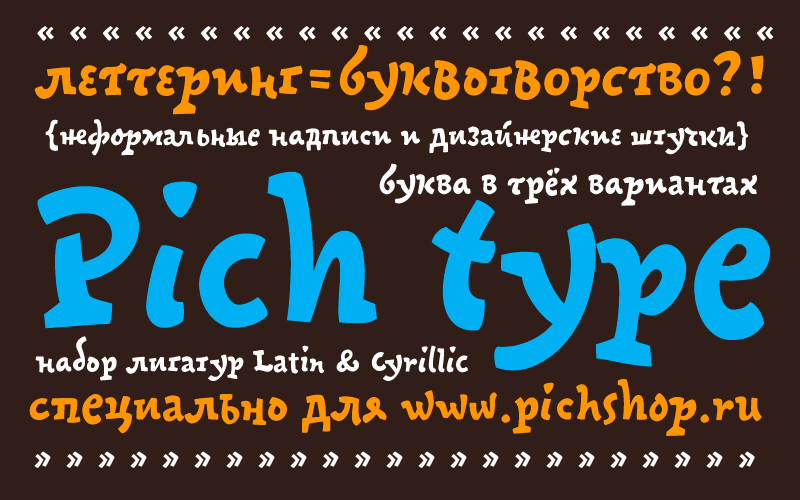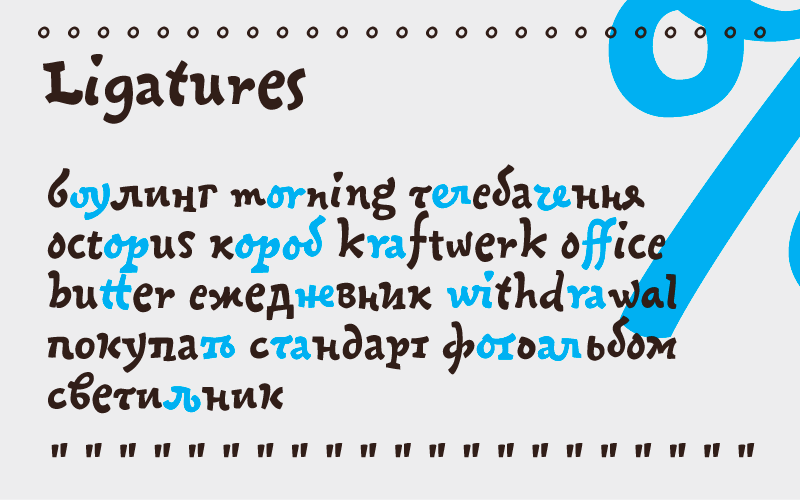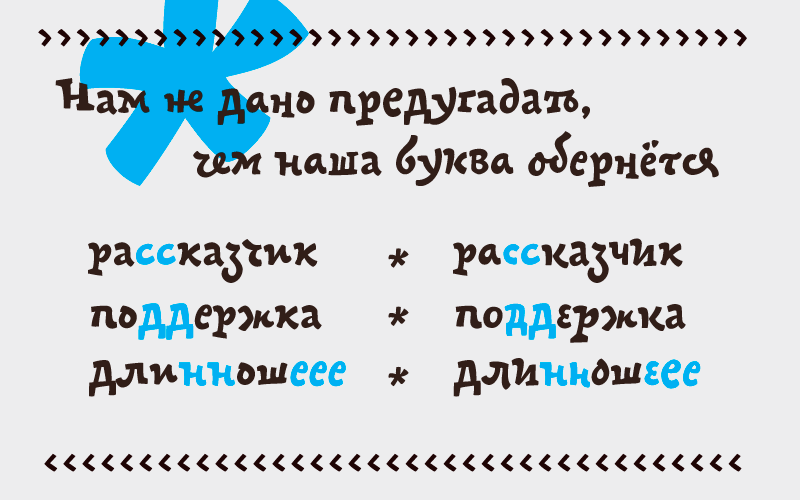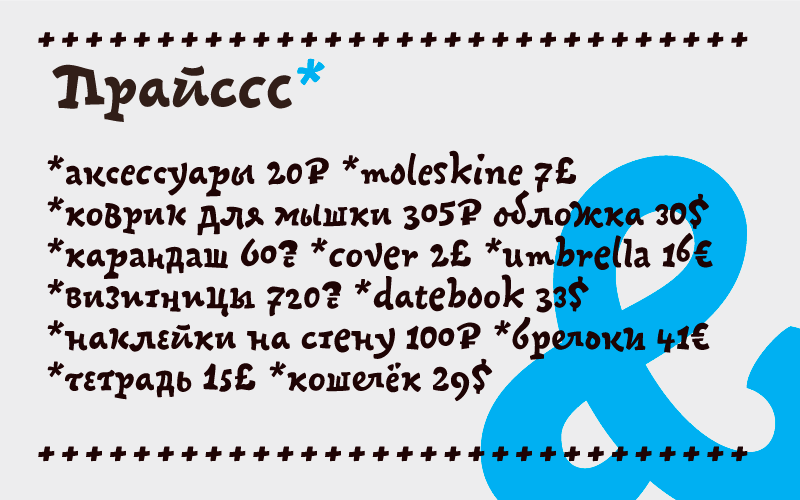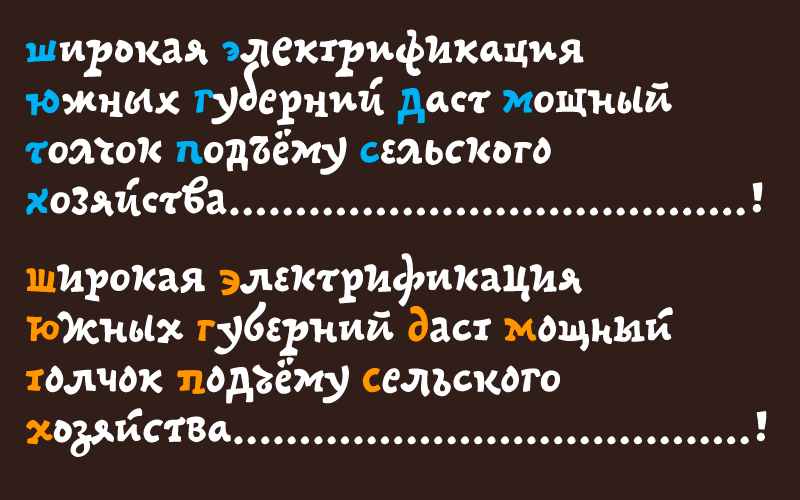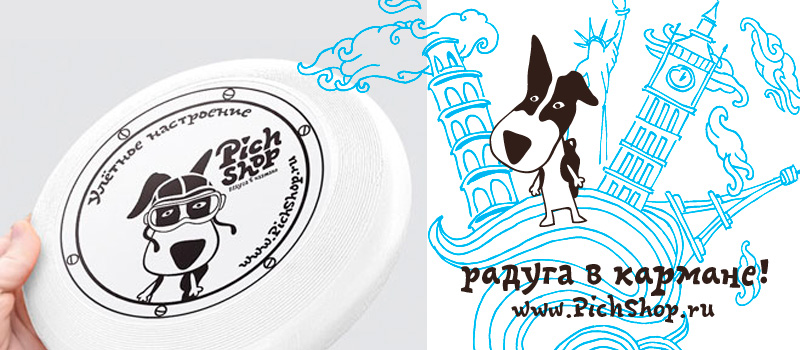
Pich
Надпись, сделанная руками, вместо набора, тёплый, местами неряшливый хэндмейд взамен чистой и обезличенной типографики—вот суть шрифта Pich.
Стояла задача спроектировать гарнитуру, при взгляде на которую оставалось бы впечатление рукотворности, чтобы читатель воспринимал буквы не как набор, а как только что нарисованную специально для него надпись. То есть сохранить прелесть леттеринга и дать возможность набирать. Для решения этой задачи была выбрана технология random type, когда графика каждой конкретной буквы произвольно меняется (или псевдопроизвольно, в зависимости от «соседей» в строке). Каждый символ шрифта имеет три варианта, что позволяет варьировать набор, делать его более шероховатым и подвижным. Кроме того шрифт включает в себя лигатуры, что ещё больше приближает его к леттерингу.
Pich разработан в 2009-ом году специально для магазина Pichshop. Логотип, персонаж и стиль Pichshopa созданы Денисом Башевым. Шрифт вошёл в Топ-100 российского дизайна по версии журнала «Как».